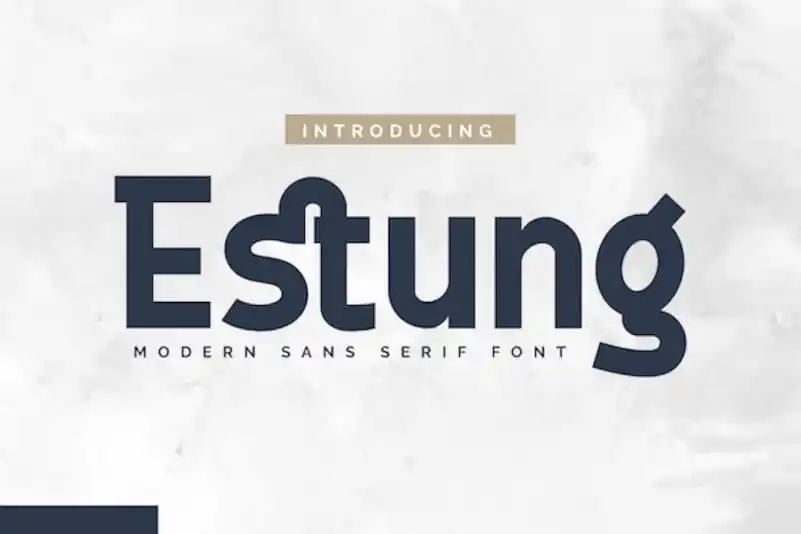
Estung Sans Serif Font – Download Grátis
A Estung Sans Serif é uma linda fonte geométrica projetada para escrever títulos e frases confortáveis ao ler. Com seu caráter único, simples e elegante, esta fonte se torna perfeita para seus design projetos variados. Flexível em sua utilização, a fonte oferece três opções conforme as suas necessidades específicas. Seja você um designer de produtos, de sites ou até mesmo de gráficos publicitários, Estung Sans Serif está aqui para enriquecer e dar vida ao seu projeto. Escolha essa versão elegante da família de fontes sans serif que pode transformar sua próxima criação de design em destaque.